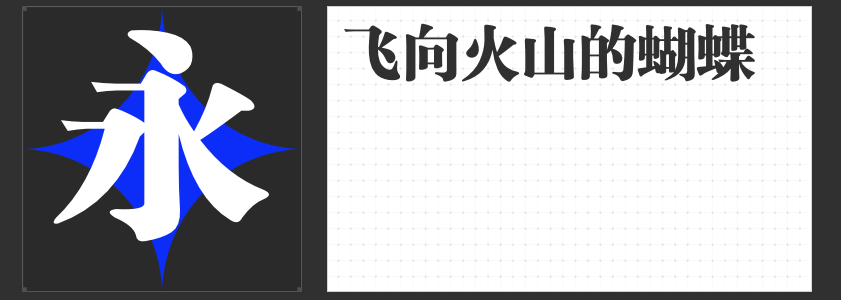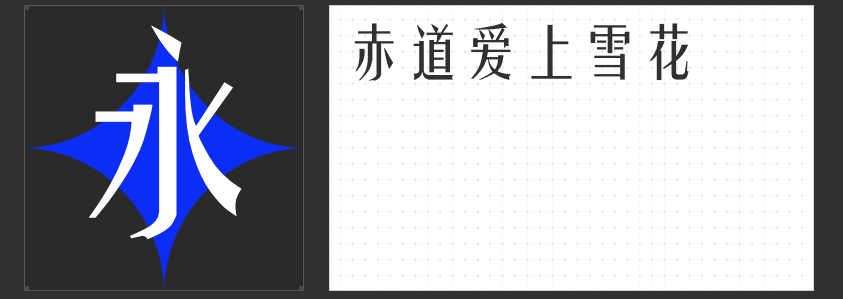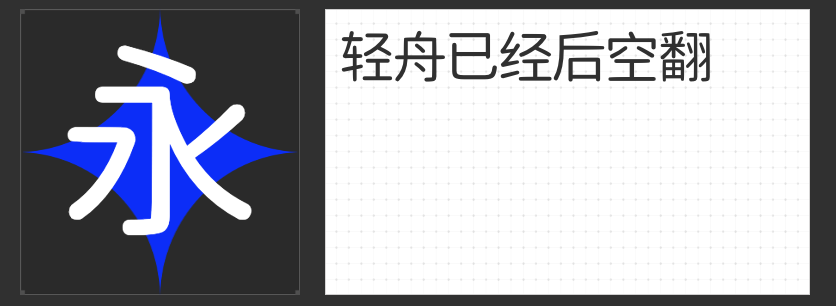
经典设计字体推荐:四款匠心之选,赋予版面独特魅力
在视觉设计领域,字体的选择是构建风格、传递情感的关键。以下四款经典字体,以独特的结构美学与文化底蕴,成为专业设计师的信赖之选。
一、励字新粗宋简
这款字体以横细竖粗的经典宋体骨架为基底,却在细节处打破传统:竖画末端延展出精致的衬线装饰,点、撇、捺等笔画以锐利尖端收笔,赋予字形动态张力。其创新之处在于字型扁方化的重构——通过压缩纵向空间,增强横向视觉延展性,既保留宋体的人文气质,又融入现代设计的几何秩序感。适用于文化海报、品牌标语等需要传递传统底蕴与现代活力的场景。
二、励字姚体简繁
融合黑体与宋体精髓的姚体,以狭长挺拔的字形重构文字的呼吸感。横竖笔画刚劲利落,转折处保留宋体的方硬骨力,却以更紧凑的间距与统一的笔画粗细,营造出隽秀工整的视觉秩序。其清瘦端庄的体态,在书籍标题、杂志专栏等需要平衡易读性与艺术性的场景中尤为出色,既能提升版面精致度,又不会喧宾夺主。
三、字圈也字万能黑体
这款黑体的独特性在于其“喇叭口”装饰——每一笔画的端口以微妙弧度向外延展,既是对早期铅字印刷技术的致敬,亦是对黑体方正之态的诗意解构。喇叭口设计打破了黑体固有的机械感,在保持字形规整的同时注入灵动气息,尤其适合科技产品海报、工业设计图册等需要平衡理性与温度的场景,让文字成为技术与人文对话的媒介。
四、励字励黑简
作为无衬线字体的极致呈现,励黑简以超粗笔画与方正结构构建视觉重音。其笔画粗细完全统一,起笔方头如刀刻般利落,折笔处舍弃字肩设计,形成浑然一体的块面感。这种去繁就简的造型语言,使其成为书刊封面标题、户外广告等需要强冲击力场景的首选,以最纯粹的几何语言传递信息,在喧嚣的视觉环境中瞬间抓住眼球。
四款字体虽风格迥异,却共享着对文字美学的极致追求:或重塑传统,或追溯历史,或探索未来,皆以匠心设计为设计作品注入不可复制的灵魂。选择它们,即是选择一场跨越时空的字体对话。